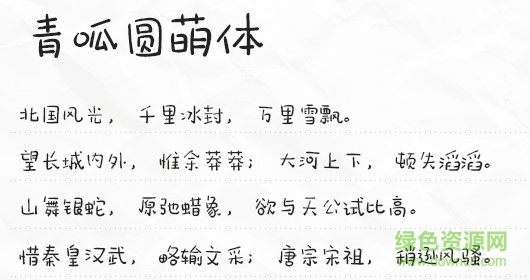
软件介绍 软件标签: 青呱圆萌体 卡通字体 青呱圆萌体是一款十分q萌可爱的卡通字体,造型圆润而活泼,让人体验生动有趣的视觉呈现,喜欢的朋友千万不要错过,快来绿色资源网试试吧!青呱圆萌字体特色青呱圆萌体造型小巧而有趣,风格上有着手写字体的恣意和简约,结构完整,没有中规中矩的严肃,自称一派,给大家的平面设计、艺术设计带来更多悦目体验!青呱圆萌体ttf字体使用单个字体安装较为简单,在本站下载解压后,运行字体文件,点击安装即可。批量安装字体,直接将字体ttf文件复制粘贴到C:\Windows\Fonts文件夹即可完成安装。安装完成后,字体名称在系统中正好对应中文名称,打开你的办公软件即可使用了! 软件截图 上一张下一张(1 / 1) 安装详细截图 猜你喜欢 卡通字体 卡通字体 卡通字体一般都比较可爱、秀气,很多MM都很喜欢,许多公主体、萝莉体非常适合女生使用。类似卡通风格的字体有很多,其中最出名的就是华康少女字体了,还有华康童童体、娃娃体都很独特。本站制作的卡通字体下载大全,为喜爱卡通字体的朋友们收集整理了各种新颖、可爱、活泼的卡通字体,都是免费的,大家可以随意选择下载。 查看更多>> Aa小云朵想吃糖 5.90M/中文/10.0/ttf版下载 aa小软糖字体 4.37M/中文/10.0/下载 软萌甜心字体 18.26M/中文/10.0/ttf免费版下载 双初千草体 10.78M/中文/5.0/下载 花花爱彩虹字体 14.13M/中文/6.6/下载 小兔子乖乖体字体 1.75M/中文/2.0/下载 其他版本下载 标题 大小 更新日期 下载 下载地址 电脑版 青呱圆萌字体 点击报错 软件无法下载或下载后无法使用,请点击报错,谢谢! 关闭报错反馈 请描述您所遇到的错误,我们将尽快予以修正,谢谢! *必填项,请输入内容 本类最新 dreamweaver字体库 首尔南山体字体 v1.06 官方版 潮字社风云简ttf 潮字社凌渡鲲鹏简体字体 潮字社曾玉波手书简字体 微博慧心字体 相关文章 Photoshop字体安装使用方法和技巧 如何解决“无法新增字体”问题 Win 7系统安装字体方法 网页字体大小设置方法 怎么改网页字体大小 在Linux系统中安装字体的几种方法 windows7字体显示问题:打开某些程序的时候显示的是乱码 用户评论 热门评论 最新评论 发表评论 查看所有评论(0) 昵称: 请不要评论无意义或脏话,我们所有评论会有人工审核. 字数: 0/500 (您的评论需要经过审核才能显示)